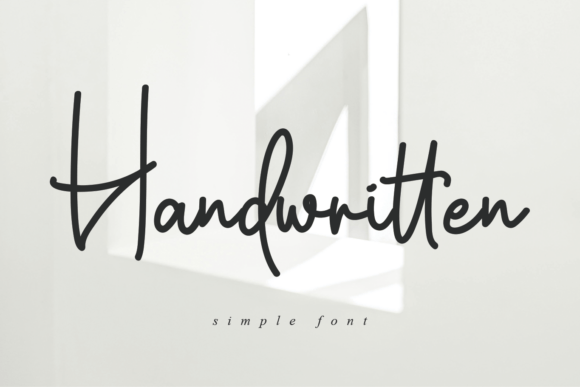
Handwritten
Handwritten : Une police manuscrite raffinée pour un style contemporain
Si vous cherchez une police manuscrite qui allie élégance intemporelle et fraîcheur moderne, Handwritten est l’option idéale. Cette police mince, inspirée de la calligraphie classique, se distingue par son style unique et son côté chaleureux. Elle incarne l’équilibre parfait entre tradition et innovation, ce qui en fait un choix incontournable pour les projets créatifs.
Caractéristiques principales de Handwritten
- Lettrage fin et raffiné : Les traits sub